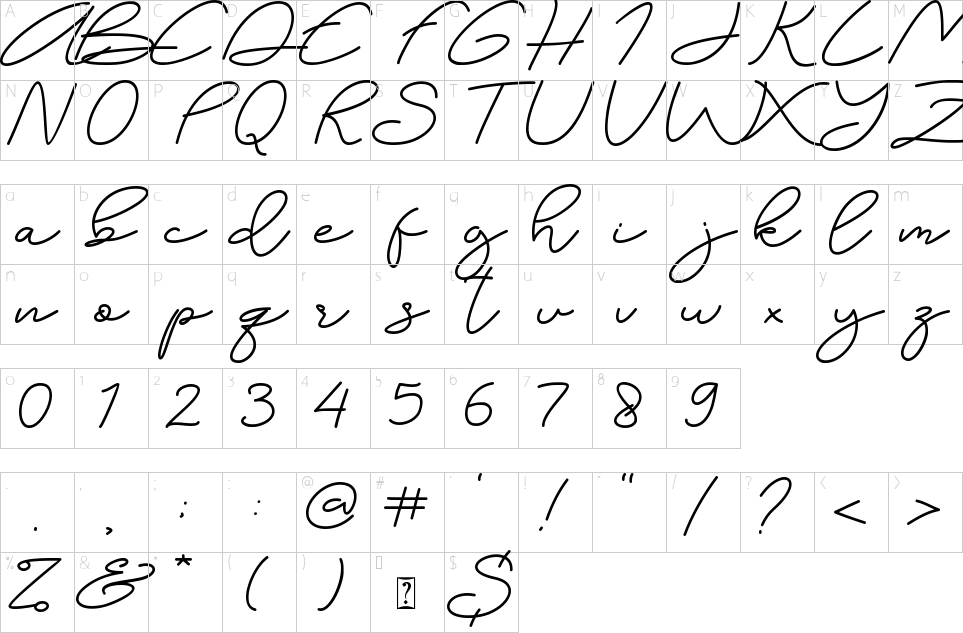
A Angelista é uma fonte cuidadosamente criada pelo estúdio Nox Studio, disponível gratuitamente tanto para Windows quanto para Mac. Suavemente fluida e com um toque de elegância, essa fonte é perfeita para dar um toque personalizado a qualquer projeto de design. Com 1,824 downloads, você pode garantir que ela seja uma escolha confiável para sua próxima obra de design. Sua simplicidade e capacidade de se adaptar a vários estilos de design tornam-a uma fonte versátil que encaixa-se perfeitamente em qualquer projeto. Se você está procurando por uma fonte gráfica de alta qualidade que não custa nada, a Angelista é uma excelente escolha.